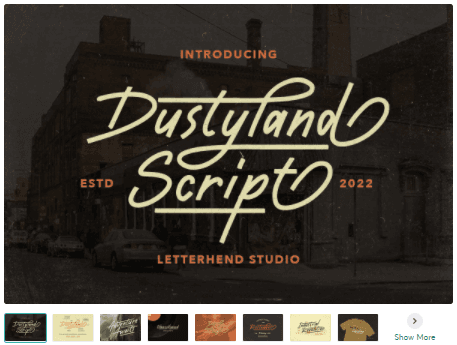
Dustyland Script Font
Dustyland Script — это монострочный скрипт с оттенком винтажного стиля. Этот тип шрифта идеально подходит для использования, особенно в логотипах, заголовках, вывесках и других различных формальных формах, таких как приглашения, этикетки, логотипы, журналы, книги, поздравительные / свадебные открытки, упаковка, мода, макияж, канцелярские товары, романы, этикетки или любые рекламные цели.